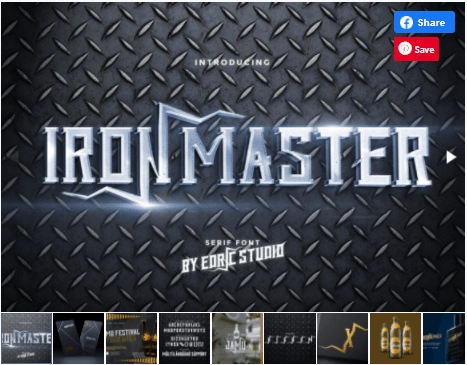
Iron Master Font
Iron Master — это крутой, жирный шрифт с толстыми буквами. Он идеально подходит для написания веб-дизайна, визитных карточек или почти всего, что требует футуристического подхода.